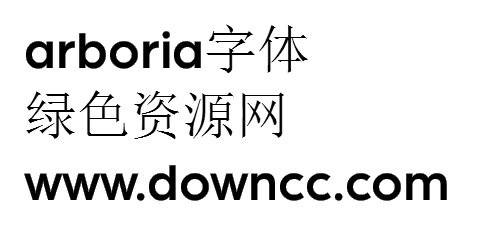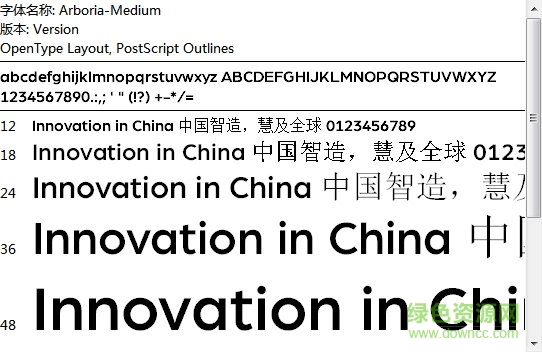
arboria medium是arboria系列字體中的中等字體,造型簡(jiǎn)潔大方,有著極佳的視覺(jué)效果和裝飾體驗(yàn),英文自帶粗黑設(shè)計(jì),使文字內(nèi)容更加醒目,快來(lái)綠色資源網(wǎng)試試吧!
arboria英文字體包括Arboria Medium、Arboria-Thin、Arboria-Light 、Arboria-Book、Arboria-Bold、Arboria-Black等,其中arboria medium是使用較為廣泛的字體,一定程度的粗黑設(shè)計(jì)讓文字更加顯眼,容易抓住讀者的眼光。
arboria medium在英文領(lǐng)域的使用上,較為嚴(yán)謹(jǐn)而莊重,給文字一種嚴(yán)肅的表達(dá)態(tài)度,造型結(jié)構(gòu)上大方樸素,無(wú)多余的點(diǎn)綴,讓文字得以清晰呈現(xiàn)本來(lái)的韻味,可以使用在平面設(shè)計(jì)、廣告策劃、ppt制作、課件教案等多個(gè)方面!